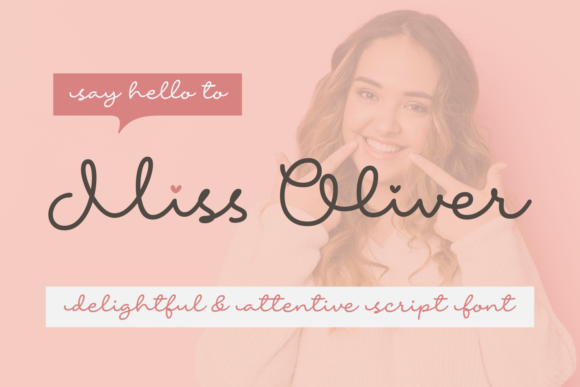
Miss Oliver
إذا كنت تبحث عن أصول عالية الجودة مثل Miss Oliver، فإن هذه الحزمة المميزة هي خيار رائع لمشاريعك الإبداعية.
سواء كنت تقوم بإنشاء منتجات الطباعة عند الطلب أو دعوات الزفاف أو رسومات وسائل التواصل الاجتماعي، فإن Miss Oliver هو الخيار المثالي.